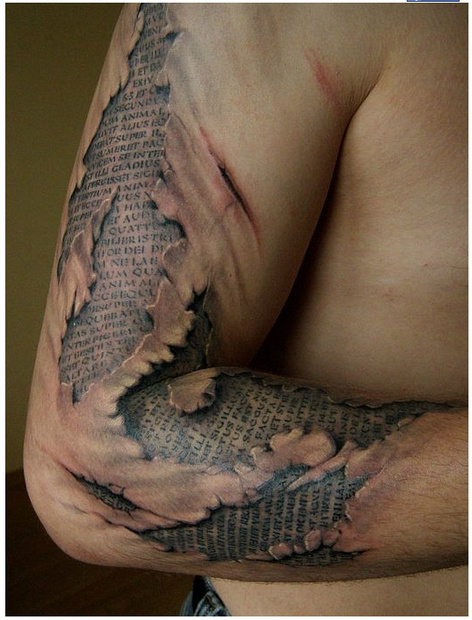
… (hier gefunden)
(Hier haben wir schon einige tätowierte Grauslichkeiten zusammengetragen …)
wunderschön! ganz herzlichen dank für diese bilder, itob (und pachulke). herrlich hintersinnige dinge tun sich da an meinem bildschirm ;) mein persönlicher favorit ist die fastfoodverfettung.
Als ich an dem Schild vorbeifuhr, dachte ich erst, ich hätte mich verguckt, doch auf der Website des Unternehmens finde ich das gleiche:
Es soll Eschner heißen, doch das Logo sagt mir „Etschner“.
Da wollte es der Kunde wohl lieber hübsch als funktional haben. Vielleicht ist die Unterzeile »Willkommen bei Eschner-Immobilien« schon so ein Mittel zur Schadensbegrenzung, weil dauernd Leute am Telephon nach dem Herr Etschner verlangt haben.
Ich würde ihn ja "Undschner" nennen. :peng:
etschner. krass. dass die das so stehen lassen … schaut ja auch aus! die immokrake dringt bis unters dach. hüten sie ihre geheimnisse im keller! tsss.
Die Blechschachtel des Farbstifts Cartograph 541 von Eberhard Faber (vermutl. 1940er Jahre):
Mir gefällt der Schriftzug „Cartograph“ ausgemacht gut. – Weitere Bilder gibt es in meinem Weblog (ich hoffe, diese Eigenwerbung geht hier in Ordnung).
1940 ... schlägt sich auch im auf der Verpackung dargestellten Kartenbeispiel wider: militärische Stellungen zweier Kriegsparteien um eine umkämpfte Ortschaft herum.
PS: eben durch Zufall entdeckt ... ich meinte einen Apostelkuchen mit einem frisch gebrühten Kaffee, aber es gibt auch eine Schrift Brioche http://jessicahische.bigcartel.com/product/brioche-font
:peng:look at this one. available in 3 kinds (thanks to d. s. on facebook).